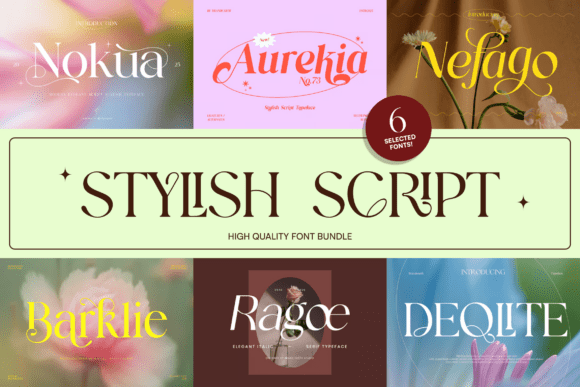
Stylish Script Bundle
Если вы ищете высококачественные ресурсы, такие как Stylish Script Bundle, этот премиум-пакет — фантастический выбор для ваших творческих проектов.
Создаете ли вы продукты POD (печать по требованию), свадебные приглашения или графику для социальных сетей, Stylish Script Bundle станет идеальным выбором.